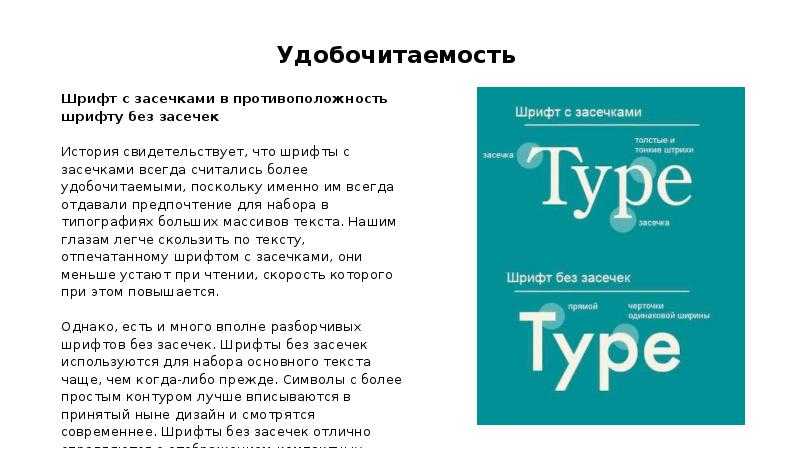
Как выбрать шрифт для проекта если ты новичок
Трудно подобрать шрифты для своего проекта? Тогда вы по адресу. В статье рассказывается о нескольких базовых принципах, которые помогут новичкам и не только создать гармоничный дизайн с текстом. Так же вы узнаете, как быстро найти шрифтов пару.
Текст – это самый популярный способ передачи информации, знакомый каждому!
В дизайне сайтов, мобильных приложений и рекламных плакатов чаще всего именно текст транслирует главную коммерческую мысль проекта. И от того, насколько правильно он будет представлен, зависит положительная реакция аудитории.
Текст может стать центральным объектом дизайна, вокруг которого уже строятся другие элементы – изображения, ссылки, иконки.
Пример использования крупной надписи в дизайне сайта violin-rio.dance
Текст и типографика – искусство его оформления – нужны, чтобы передать большие объемы информации. На первом плане здесь простота чтения.
Начинающим дизайнерам трудно выбрать шрифт. Используя следующие советы, вы можете повысить качество своих работ.
Использование одного шрифта в проектеКогда решаете, какие шрифты использовать, помните – чем проще, тем лучше. Для начала ограничьте себя одним шрифтом на проект.
«Человеческий мозг не способен воспринимать более восьми элементов одновременно, и как только это количество увеличивается, внимание начинает рассеиваться. Выдержанное, концептуальное объявление бросается в глаза за счет строгой̆ типографики. Никаких экспериментов — берите классический̆, испытанный̆ шрифт, делайте привычный̆ макет, и адресат прочтет ваше сообщение.
»
«Что может быть проще и строже шрифта Futura»
(Эрик Шпикерман, «О шрифте»)
И действительно, разработанное более 70 лет назад семейство шрифтов, до сих пор остается популярным среди дизайнеров, олицетворяя немецкую строгость и сдержанность.
Если используете один шрифт в дизайне, меняйте его размер, стиль, начертание. Получится интересная, читаемая комбинация.
Советы по выбору шрифтовой парыПри выборе двух шрифтов, помните, что они должны дополнять друг друга. Графичный шрифт для заголовков и более простой для остального текста или наоборот, крупный простой шрифт для заголовка (например, Futura) и более экзотичный для остального текста. Таким образом получается шрифтовая пара.
В примере используются шрифты Helvetica Neue и Savoye LET
Одно из самых распространенных правил поиска шрифтовой пары это — шрифт с засечками для заголовков и без засечек для остального текста.
Популярными шрифтовыми парами в сочетании «заголовок – текстовый блок» по мнению успешного графического дизайнера Ярослава Трегубова являются следующие:
- Times New Roman – Arial
- Roboto Slab – Roboto
- PT Serif – PT Sans
- Noto Serif – Noto Sans
- Impact – Arial
- Georgia – Verdana
Комбинаций может быть намного больше. В статье приведены самые популярные.
Как быстро подобрать шрифтовую паруДля того, чтобы быстро подобрать шрифтовую пару воспользуйтесь сервисом Google Fonts. Покажу, как это работает.
Откройте сайт и выберите карточку шрифта, которому ищите пару, например, Oswald.
Найдите вкладку Pairlings и посмотрите, какие варианты подобрал для вас Google. В данном случае это шрифты: Roboto, Open Sans, Lato, Monserrat и Source Sans Pro.
Щелкая по каждому из этих шрифтов, открывается карточка с парой. Вы можете переставлять варианты, менять их начертание и смотреть, что получится.
На рисунке выше можно видеть пример сочетания шрифтов Oswald и Open Sans.
Естественно, Google будет подбирать шрифты, которые находятся в его базе. Тем не менее данный инструмент очень полезен для понимания того, как сочетаются шрифты и поиска наилучшей пары.
Бесплатный сервис для выбора шрифтовой пары.Я стараюсь обращать внимание на сайты и сервисы, призванные помочь дизайнерам в их работе. Одним из них является сайт heyreliable.com, где можно подобрать шрифтов пару из экземпляров с Google Fonts.
Там собрано 50 вариантов сочетаний разных шрифтов. Причем очень удачно.
Такие пары отлично подойдут для дизайна мобильных и веб проектов, а так же брошюр, журналов и других видов полиграфии.
Для новичков данный сервис послужит отличным примером того, как можно сочетать шрифты.
Шрифт и характер текстаШрифты имеют собственный язык и помимо текста несут в себе определенную информацию. Важно помнить о том, какую мысль вы хотите передать с помощью текста и выбирать подходящий по характеру шрифт.
В следующем примере косой шрифт с засечками вряд ли ассоциируется с профессией программист и больше похож на мультяшный. А вот прямой шрифт справа выглядит более технологичным.
Настоящим любителям шрифтов может быть интересно увидеть простую диаграмму основных частей символа шрифта.